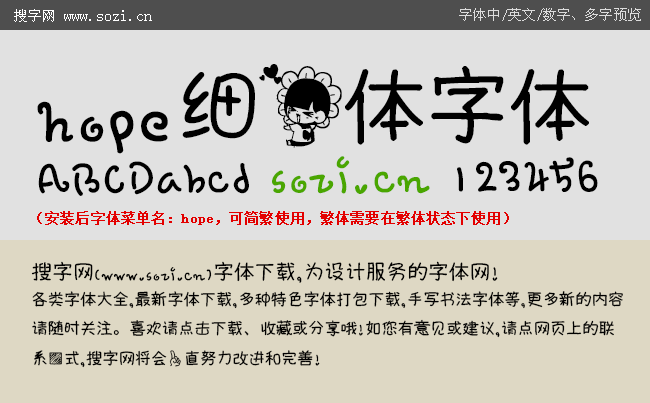
hope細(xì)花體字體
搜字網(wǎng)給大家提供一款很卡通的手機中文字體下載。修改者將它命名為hope細(xì)花體字體,這款手機字體是以仿照兒童手寫風(fēng)格的卡通手寫字體為原形,將個別字和筆畫替換成了可愛的卡通圖案。即有卡通字體的趣味性,又有手寫字體的藝術(shù)性,特別適合喜歡手機字體個性一些的朋友在手機上安裝使用。